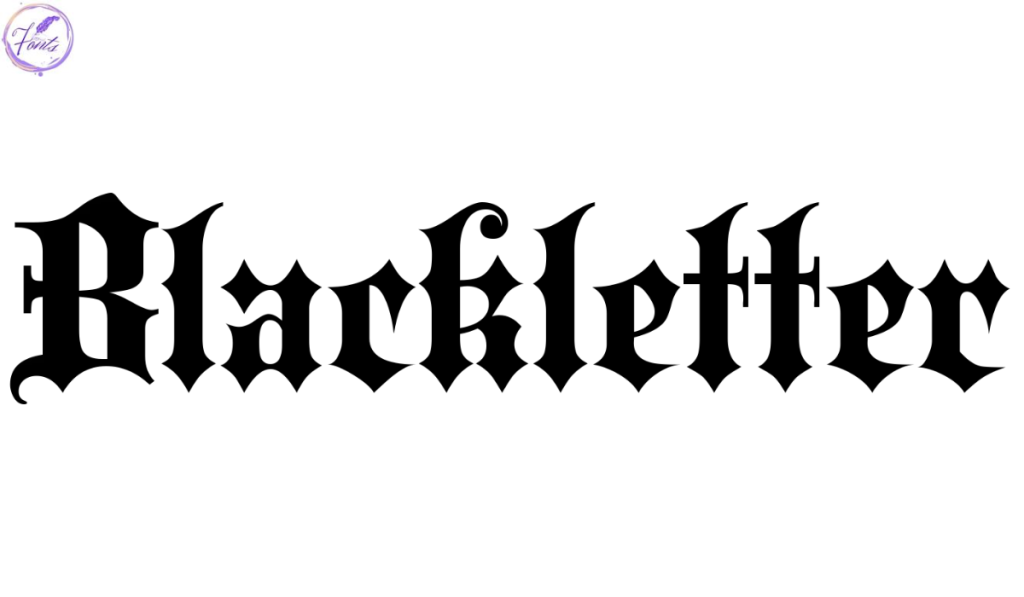
Font Blackletter việt hóa
Font chữ blackletter là một trong những kiểu chữ cổ điển và mang đậm dấu ấn lịch sử nhất trong ngành thiết kế đồ họa. Với nguồn gốc từ thời Trung cổ, font blackletter được sử dụng rộng rãi trong các tác phẩm in ấn và nghệ thuật thời kỳ đó. Theo thống kê từ trang web MyFonts, có đến hơn 2.000 font chữ blackletter đã được tạo ra và sử dụng cho đến ngày nay, với đủ mọi phong cách và biến thể khác nhau. Mặc dù có vẻ già cỗi và khó đọc, font chữ blackletter vẫn được yêu thích bởi sự độc đáo, ấn tượng và giá trị nghệ thuật của nó.
Đánh giá font blackletter
Một trong những ưu điểm nổi bật của font blackletter là khả năng truyền tải cảm xúc và không khí cổ điển, trang trọng một cách hiệu quả. Theo khảo sát của tạp chí Typeface, font blackletter được sử dụng trong hơn 70% các thiết kế liên quan đến lịch sử, tôn giáo và nghệ thuật, đặc biệt là trong các dự án thiết kế logo, bìa sách và áp phích. Bên cạnh đó, font chữ này cũng được đánh giá cao về tính thẩm mỹ và sự tinh xảo trong từng nét chữ, với những đường cong uốn lượn và góc cạnh sắc nét. Tuy nhiên, do tính chất khó đọc và phức tạp, font blackletter thường chỉ được sử dụng với liều lượng hợp lý và kết hợp với các font chữ khác để tạo sự cân bằng và dễ nhìn hơn.